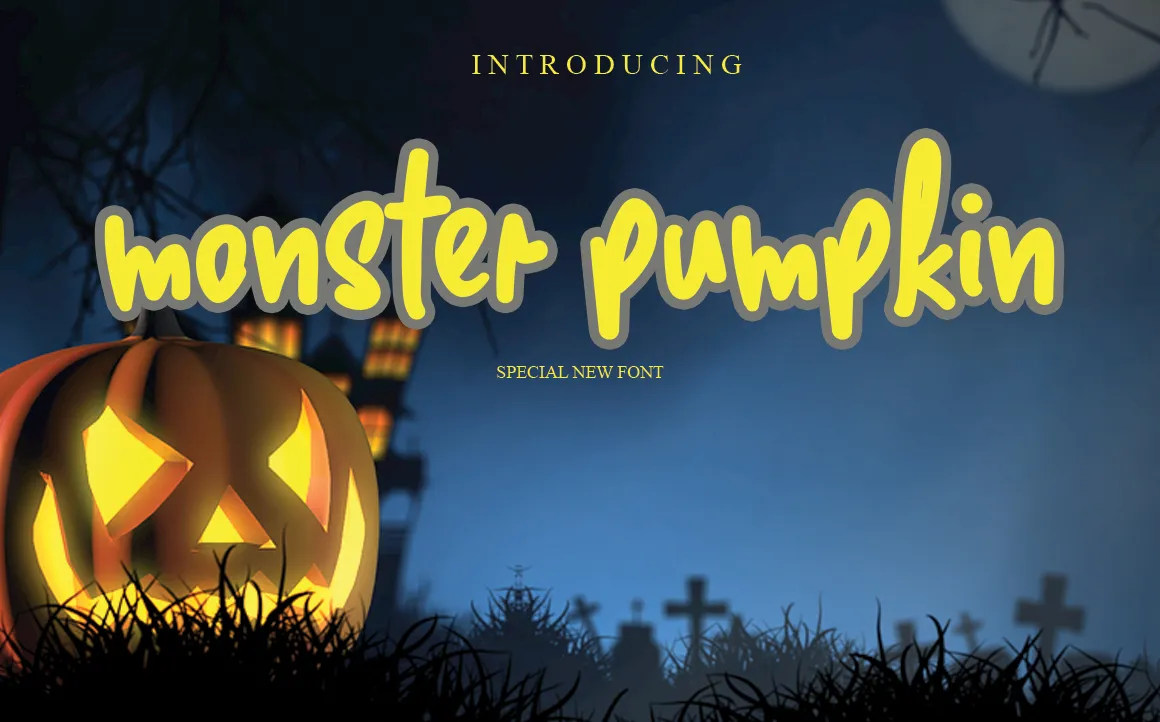
Monster Pumpkin Font – Download Grátis
A fonte ‘Monster Pumpkin Font’ é uma escolha perfeita para aqueles que buscam uma combinação única e divertida de escrita ao vivo. Especialmente adequada tanto para criações digitais como para projetos DIY, esta tipografia casual transformará suas idéias criativas em obras de arte. Seja para personalizar a sua página do Instagram ou para adicionar um toque artesanal à próxima tarefa de papelaria, essa fonte irá levar seu trabalho ao próximo nível, tornando-o autêntico e único. A proposta de design da designer LevinCreative enfatiza a simplicidade e o encanto intrínseco do estilo handwritten, garantindo que cada letra seja uma expressão natural e amigável dos seus pensamentos. Não perca essa oportunidade de dar um toque especial aos seus projetos digitais com este verdadeiro tesouro gráfico.